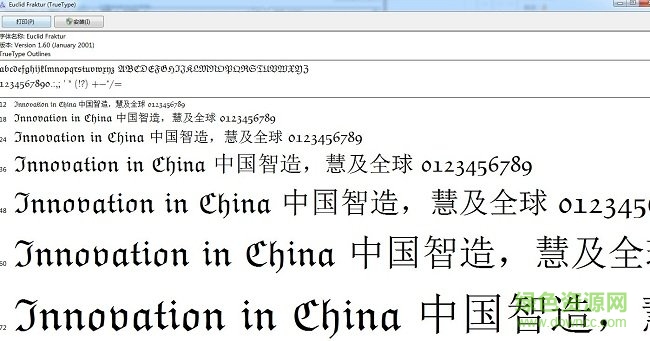
軟件介紹 軟件標簽: euclid字體 哥特式字體 euclid fraktur字體是一款字形繁復(fù)的哥特式字體,線條變化多,給人的視覺印象深刻,適合用在裝飾設(shè)計、海報設(shè)計、復(fù)古廣告、等方面,喜歡的朋友快來下載吧!哥特式字體特征哥特字體是一類印刷或手寫字體,非常華麗,哥特和洛可可都是裝飾性很強的字體,比較重視線條,花紋的變化也采用了植物做裝飾。euclid字體推薦euclid math one 授權(quán):免費軟件 WinAll, WinXP, Win7大?。?0KB語言:中文euclidmathone字體是一款實用性強的符號字體,一般mathtyp數(shù)學(xué)公式編輯器里就有這款字體,如果你的的電腦提示缺失該字體,可以在綠色資源網(wǎng)重新下載安裝!最常用中英文字體介紹【Garamond】復(fù)古傳統(tǒng),沒有強烈個性,下載地址euclid math two 授權(quán):免費軟件 WinAll, WinXP, Win7大?。?.4M語言:中文euclidmathtwo字體是一款非常有用的數(shù)字字體,支持三角形、雙杠等符號的輸入,缺失這款字體,一些文檔的數(shù)字符號就無法正常顯示,有需要者可以在綠色資源網(wǎng)免費下載!euclid類似字體推薦無襯線字體的特征無襯線體(S下載地址euclid fraktur字體安裝方法方法一:控制面板/字體/文件/安裝新字體;方法二:直接將字體復(fù)制到C:\WINDOWS\Fonts。方法三:針對win7系統(tǒng),用戶只需選中字體右鍵安裝即可。 軟件截圖 上一張下一張(1 / 1) 安裝詳細截圖 其他版本下載 標題 大小 更新日期 下載 下載地址 電腦版 euclid fraktur 點擊報錯 軟件無法下載或下載后無法使用,請點擊報錯,謝謝! 關(guān)閉報錯反饋 請描述您所遇到的錯誤,我們將盡快予以修正,謝謝! *必填項,請輸入內(nèi)容 本類最新 sounso beauty字體 spyced哥特英文字體 ttf版 zerodegrees字體 the next font ttf版 coolvetica font keep calm ttf 免費版 相關(guān)文章 我叫mt4哪個職業(yè)輸出最高 我叫mt4輸出最高的職業(yè)排行 Linux 防火墻配置基礎(chǔ)篇 解決Linux服務(wù)器下誤刪除文件問題! 使用Webmin輕松管理Linux系統(tǒng) Linux 服務(wù)器的遠程控制技術(shù)及實戰(zhàn) linux服務(wù)器異常故障解決一例 用戶評論 熱門評論 最新評論 發(fā)表評論 查看所有評論(0) 昵稱: 請不要評論無意義或臟話,我們所有評論會有人工審核. 字數(shù): 0/500 (您的評論需要經(jīng)過審核才能顯示)